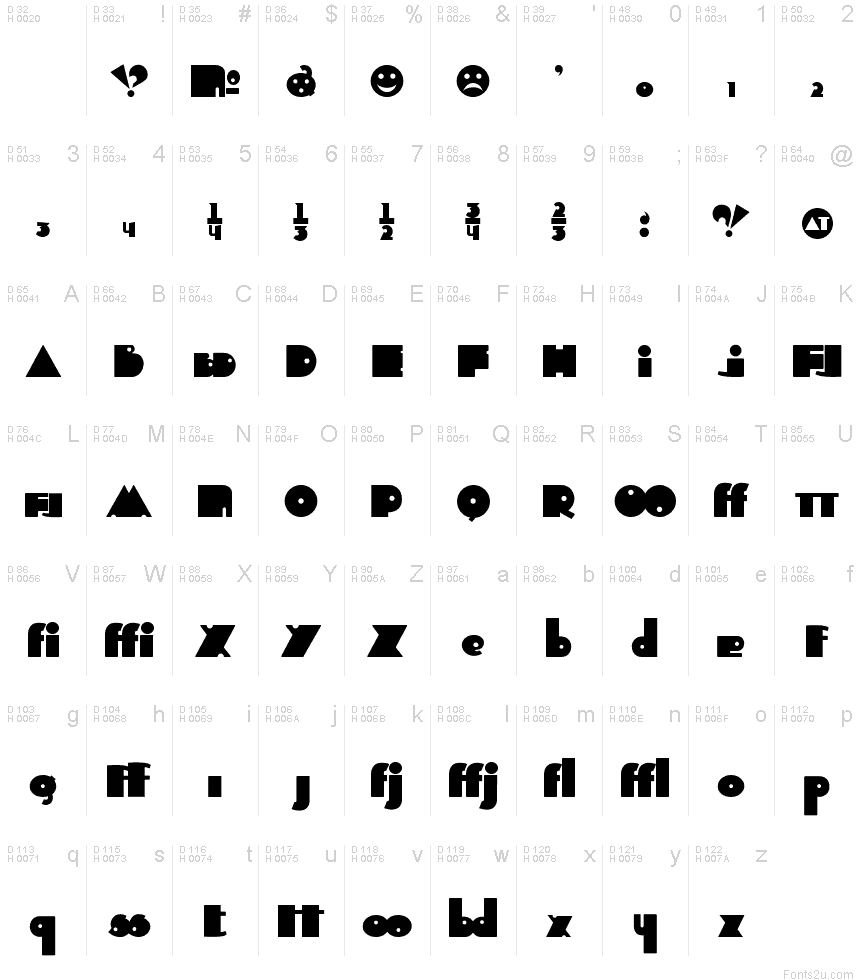
Independant Alternates od Phynette & Apostrophic Laboratories to darmowy, utrzymany w stylu retro font typu display, nawiązujący do ciężkich, europejskich szyldów z lat 30. XX wieku. Jego przerysowane, głębokie czarne kształty, okrągłe otwory i blokowe sylwetki sprawiają wrażenie niemal wyrzeźbionych, niczym litery odbite pieczątką. Rytm jest dynamiczny, lecz kontrolowany, nadając każdemu słowu śmiały, zabawny ciężar, który jest czytelny nawet z daleka.
Dzięki Independant Alternates nagłówki nie tylko przemawiają – one uderzają. Ten darmowy font świetnie sprawdza się na plakatach, ulotkach, okładkach albumów, w logotypach, na nietuzinkowych opakowaniach czy szyldach sklepowych, wszędzie tam, gdzie potrzebujesz wyrazistego, lekko ekscentrycznego charakteru. Stosuj go w dużym rozmiarze i z ciasnym kerningiem dla maksymalnego efektu, a w mniejszych tekstach pomocniczych zestawiaj z czystym, geometrycznym krojem bezszeryfowym, aby zachować czytelność i efektowny wygląd projektu.